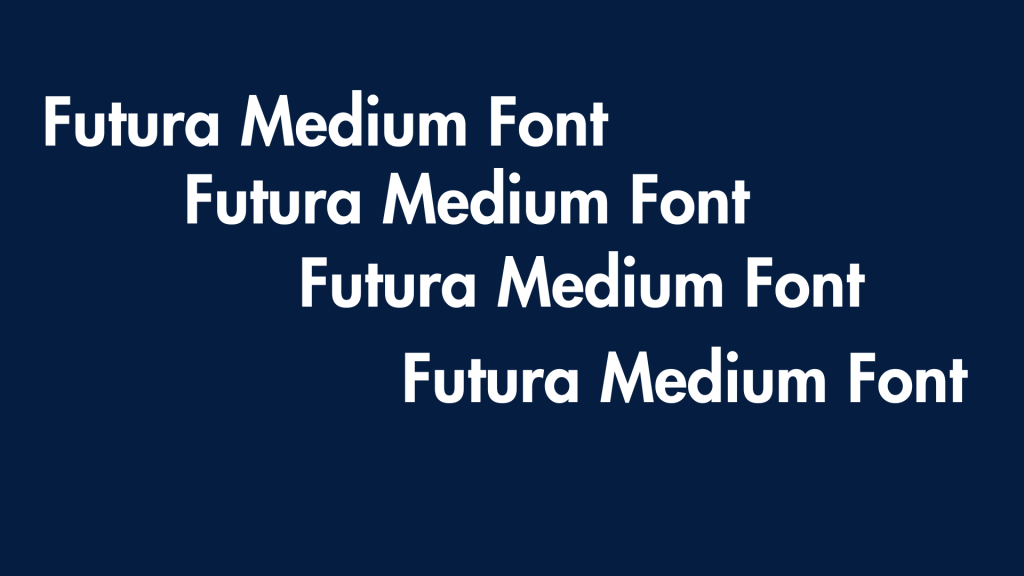
Font Futura Medium
Tác giả: Paul Renner
Ngày phát hành: 1927
Ngôn ngữ: Tiếng Anh
Việt hóa: Chưa Việt Hóa
Bộ Font: Font Futura
Phân loại: Hiện đại, Tinh tế
Độ dày: Medium, Light, Bold, Condensed
Font Futura Medium là một trong những lựa chọn phổ biến trong thiết kế đồ họa, nhờ vào sự kết hợp hoàn hảo giữa tính hiện đại và cổ điển. Với các đường nét gọn gàng, mạnh mẽ và tỷ lệ cân đối, Futura Medium thuộc bộ font chữ không chân không chỉ mang lại sự chuyên nghiệp mà còn dễ đọc trên nhiều kích thước và nền khác nhau. Được sử dụng rộng rãi trong các dự án từ logo, tiêu đề, đến văn bản nội dung, font chữ này luôn là một lựa chọn ưu tiên cho những ai tìm kiếm sự tinh tế và hiệu quả trong truyền tải thông điệp.